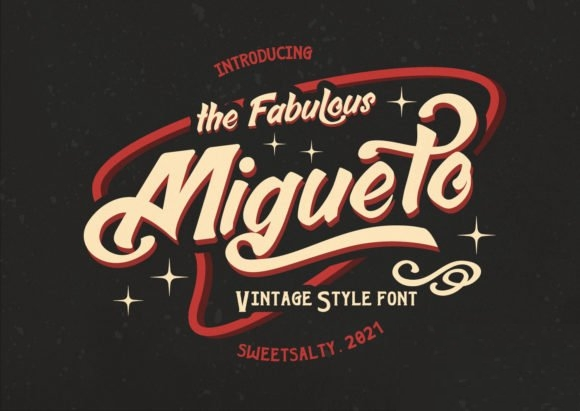
Migueto - это великолепный и смелый шрифт, созданный для придания стильности вашим заголовкам и логотипам.
Этот шрифт читается как сильный, уверенный и динамичный и может добавить тонны ностальгического характера в ваши проекты.
Migueto закодирован PUA, что означает, что вы можете легко получить доступ ко всем глифам и штрихам!